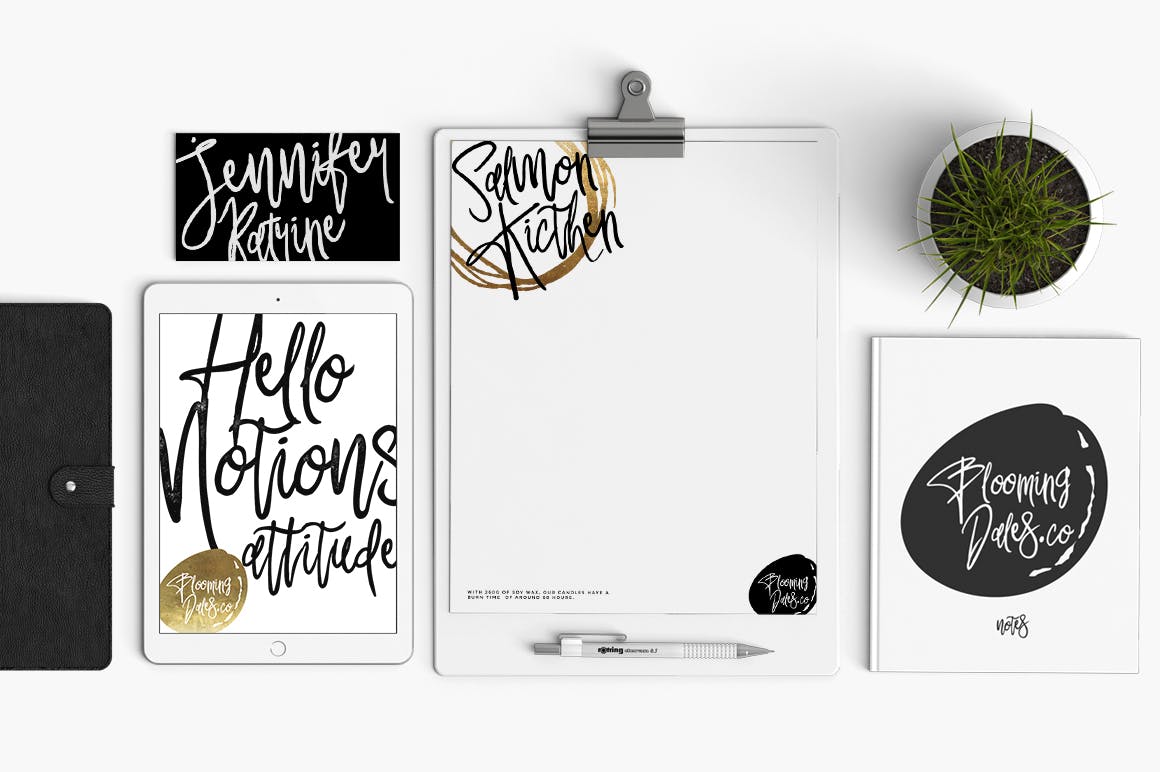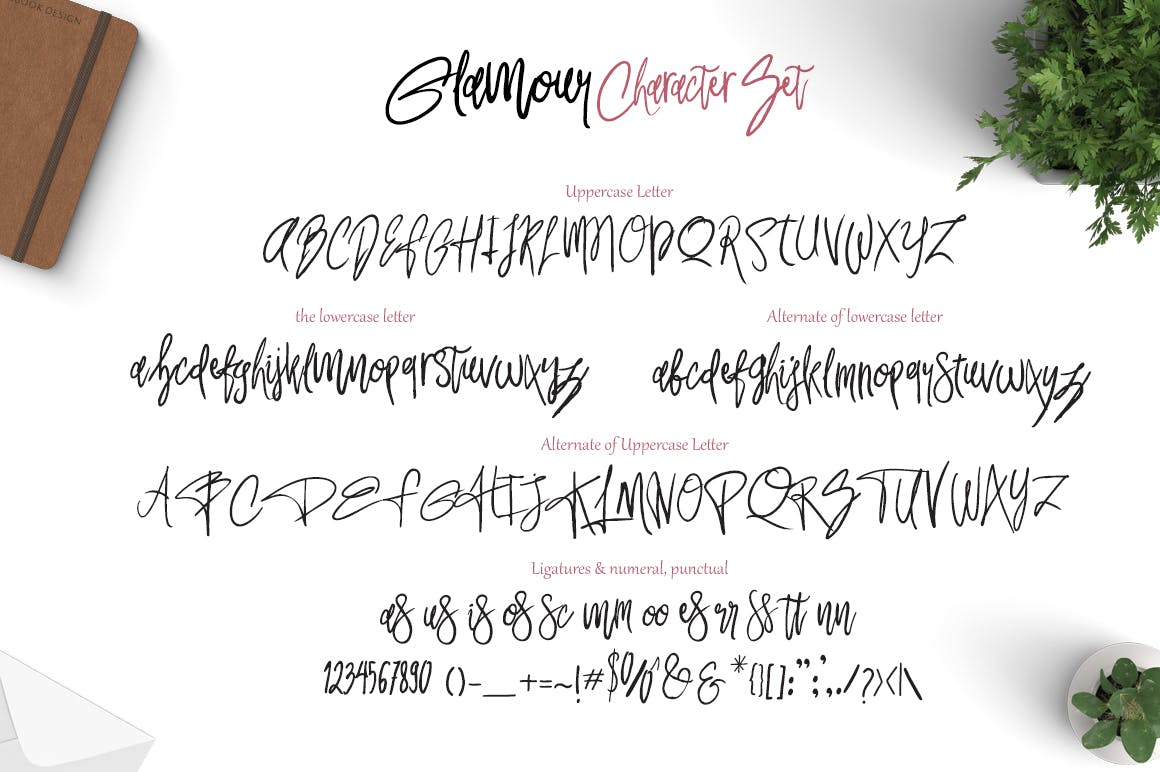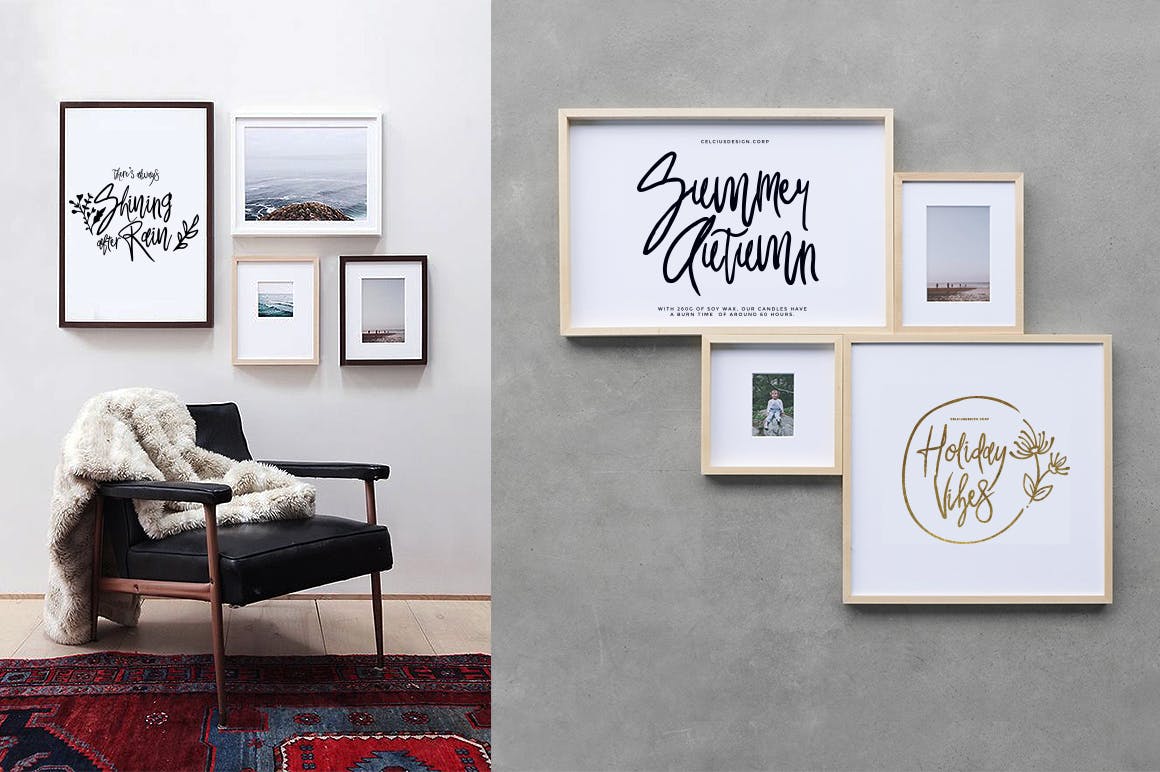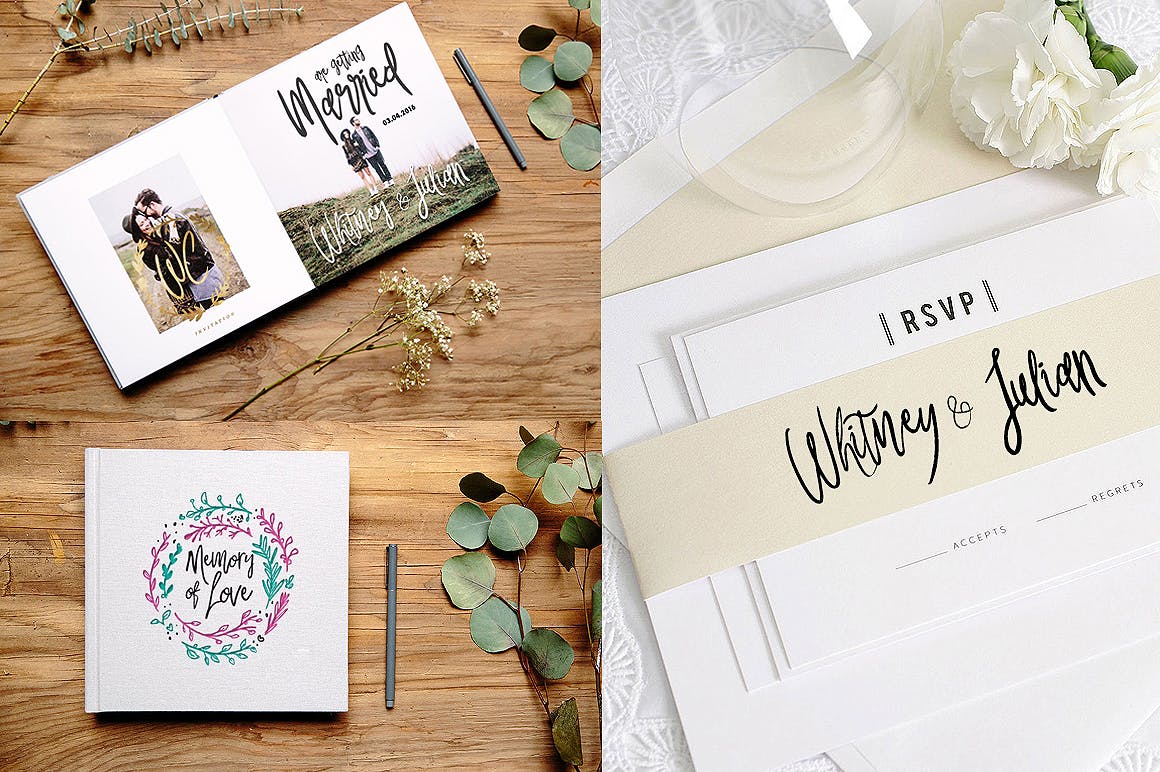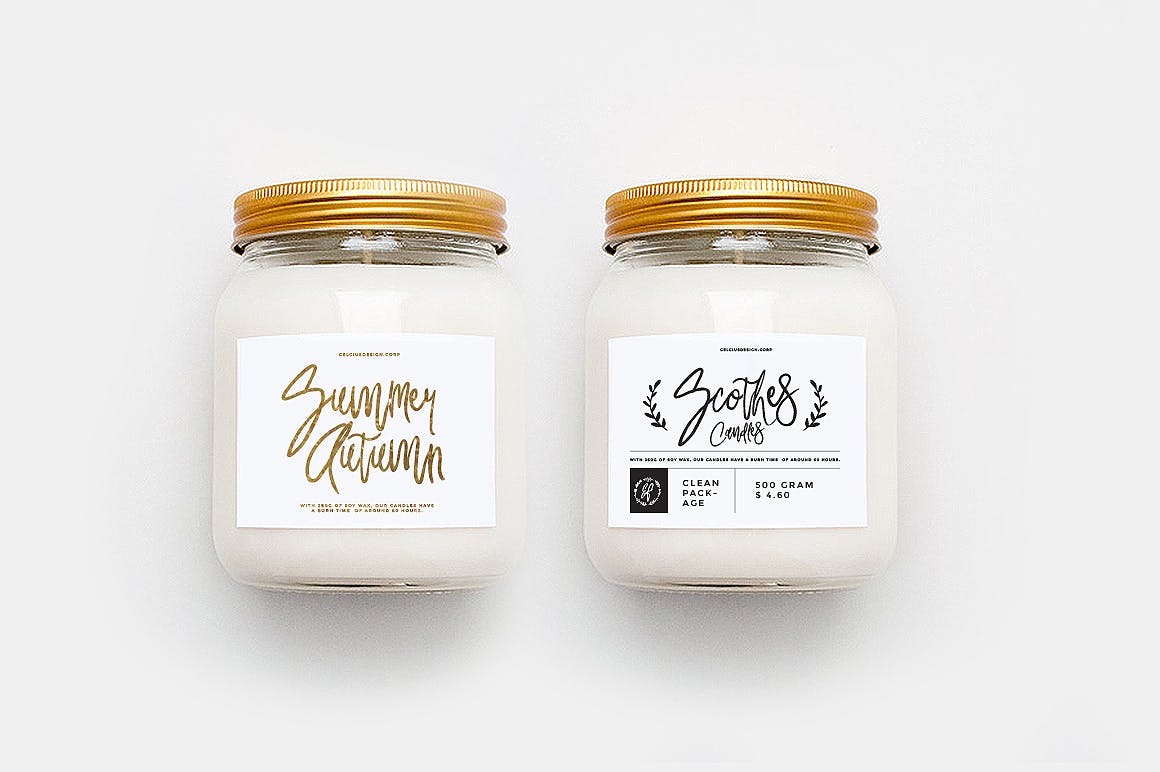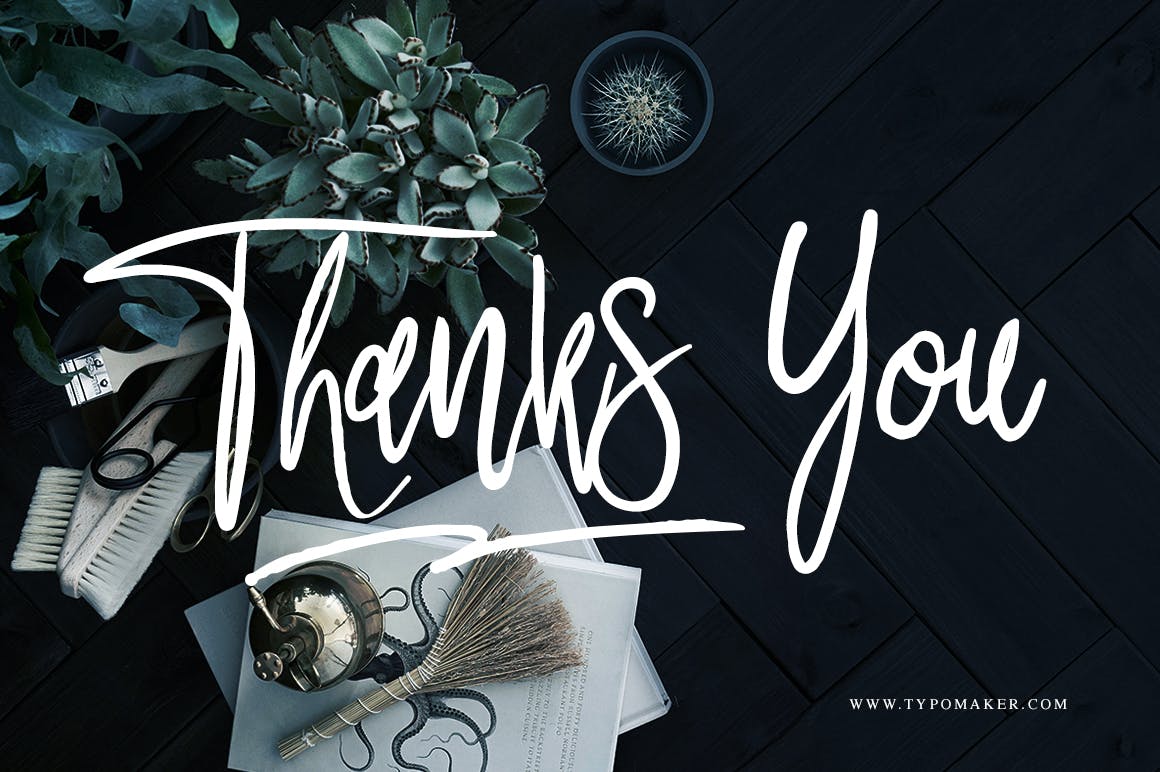
فونت Glamour & Beauty یک نوع خط امضا دستساز و آزاد است که برای طراحی وبلاگ، عنوان پروژههای DIY، لوگو، بستهبندی، لباس، غذا، دعوتنامه عروسی و برندینگ مناسب میباشد. این فونت شامل 90 لوگوی آماده و 10 الگو است که به شما امکان میدهد طراحیهای فوقالعادهای با مجموع 100 فایل مختلف ایجاد کنید.
فونت Glamour & Beauty در دو سبک حروف کوچک (جایگزینهای استایلی) با ligatures در دسترس است. فایلهای اصلی شامل: